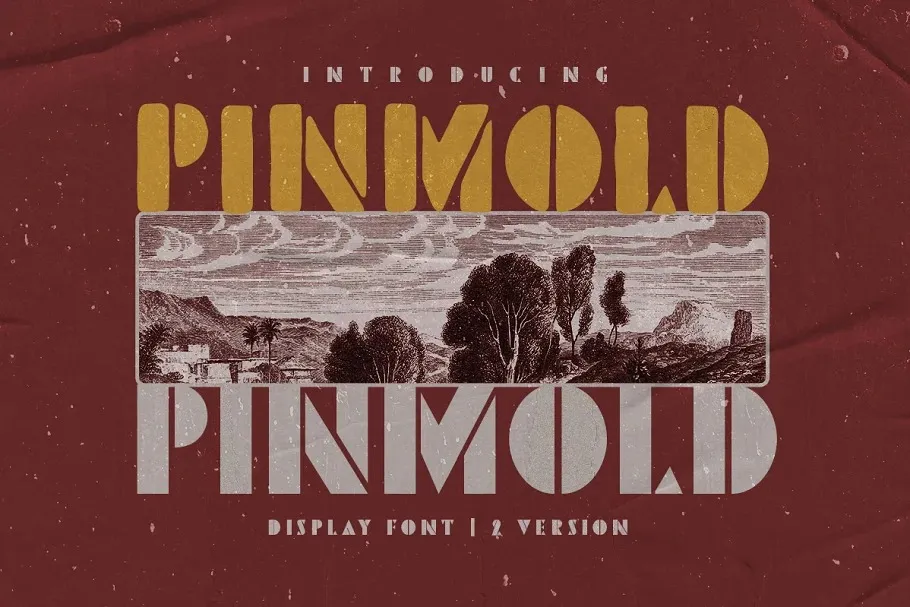
Pinmold Font
Esta é uma fonte de exibição stencil que traz ambas as características do retro e da bold. Suas curvas elásticas dão ao tipo uma sensação vintage dos anos 70, enquanto os detalhes reforçados (serifs) remetem à tradicionalidade. Este tipo de fonte é perfeitamente adequado para ser aplicada em logomarcas, headlines e sinalização, bem como outros formatos formais como roupas, livros, marcas / embalagens e diversas finalidades publicitárias. Agora, imagine-se usando esta font no seu próximo projeto gráfico: seja criando uma logo moderna com toques vintage ou projetando uma camisa de moda desse momento 70s retrô. Ou talvez seja por meio de um livro ilustrado repleto de estilo retro que transmite emoção, ou mesmo na embalagem de um produto de alta qualidade para deixar uma marca forte e duradoura no mercado. Esta fonte é sua ferramenta perfeita para estilos inovadores e criativos, ajudando você a destacar seus projetos em qualquer formato de comunicação visual.